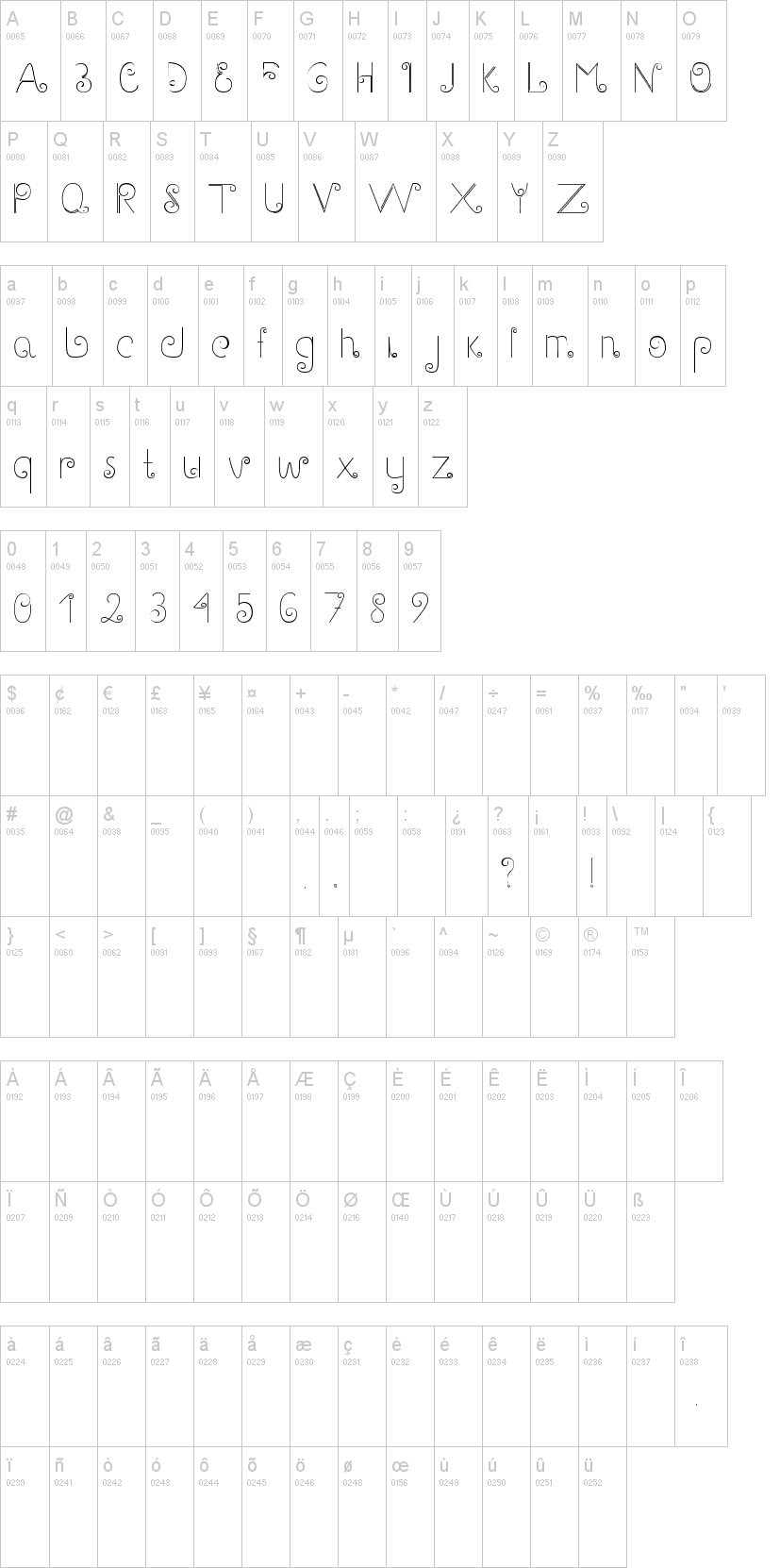
Note of the authorA Gary Script é uma fonte script inspirada nas curvas do movimento Art Nouveau.
OBS: Fonte desenvolvida como trabalho final para a disciplina de Experimentos em Tipografia Digital sob a orientação do prof. Eduardo Novais.